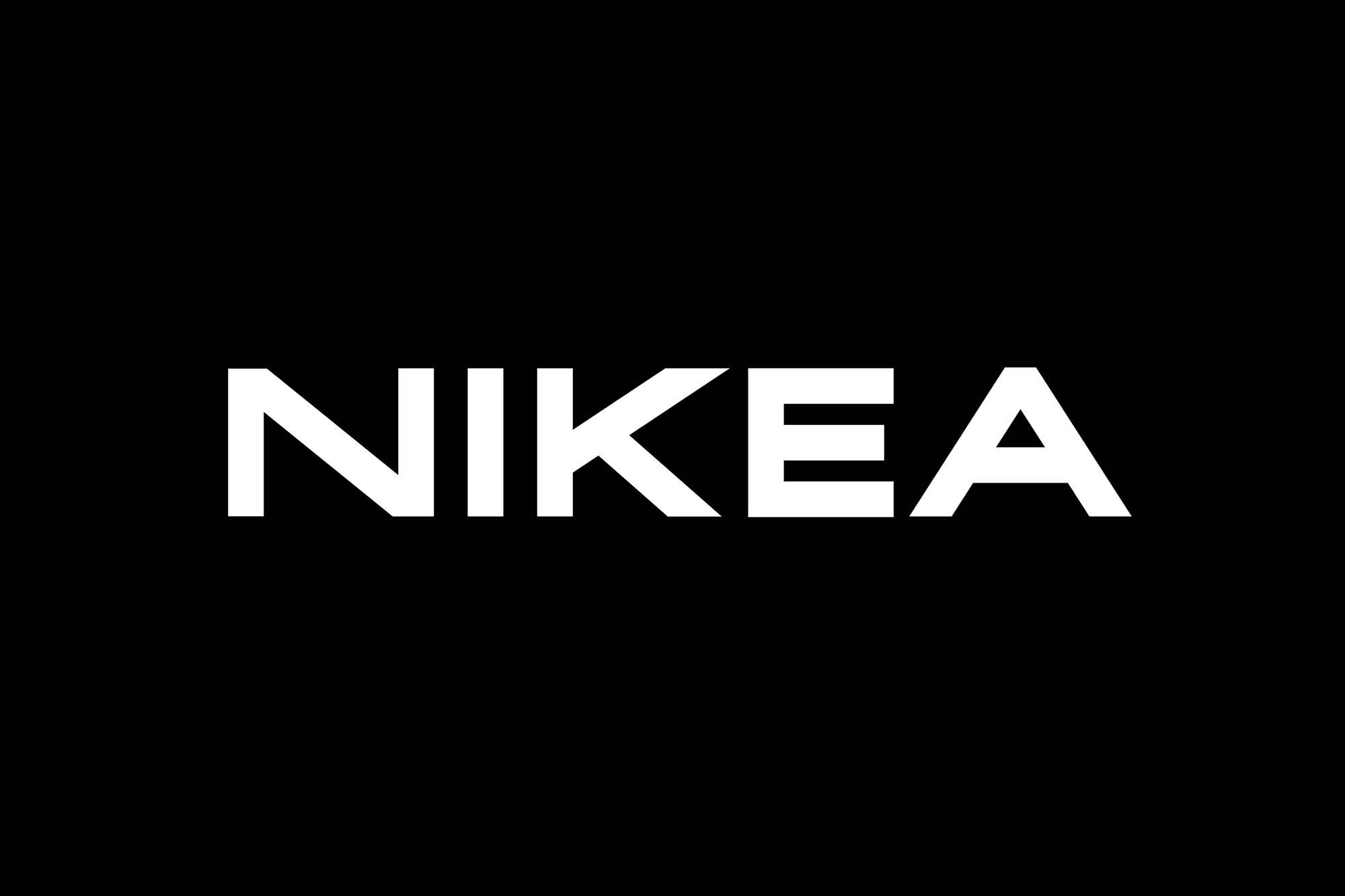
A Nikea Sans Font é uma fonte de linhas retas e contraída que destaca-se por sua equilíbrio perfeito, que vem principalmente da consistente espessura de letras. Com uma aparência elegante e versátil, ela é perfeitamente adequada para criações de marca, títulos e subtítulos, bem como embalagens. Esta fonte pode ser baixada e usada gratuitamente tanto em projetos pessoais quanto comerciais no site do autor, Limitype. A coleção inclui letras maiúsculas, caracteres especiais e números. Este recurso gráfico é uma excelente opção para estilos modernos e minimalistas, destacando-se como uma opção confiável para qualquer projeto que exija uma fonte de linhas retas e elegante.